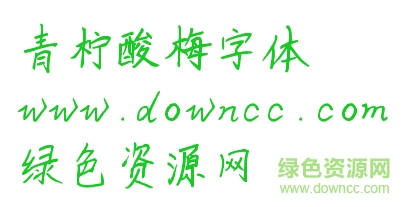
青檸酸梅ttf百度云是一款干凈清新的夏日手寫體,如初戀般美好的姿態(tài)給你最佳的視覺呈現(xiàn),深受字體愛好者和平面設(shè)計(jì)師們的喜愛,來綠色資源網(wǎng)即可第一時(shí)間體驗(yàn)哦!
本字庫是在國家標(biāo)準(zhǔn)簡體字庫GB2312所包含6763漢字的基礎(chǔ)上,又增加了近200常用字,已經(jīng)覆蓋了大陸99.75%的漢字使用頻率,足以滿足日常需求。夏天來了,喝一杯青檸酸梅汁可好?
青檸酸梅這款字體不僅非常美觀,實(shí)用性也很強(qiáng),大家可以用于很多方面,特別是藝術(shù)設(shè)計(jì)方面是很合適的,是一款適合鋼筆書法書寫的字體,可廣泛運(yùn)行于海報(bào)設(shè)計(jì)、文字印刷、廣告創(chuàng)意等行業(yè)。